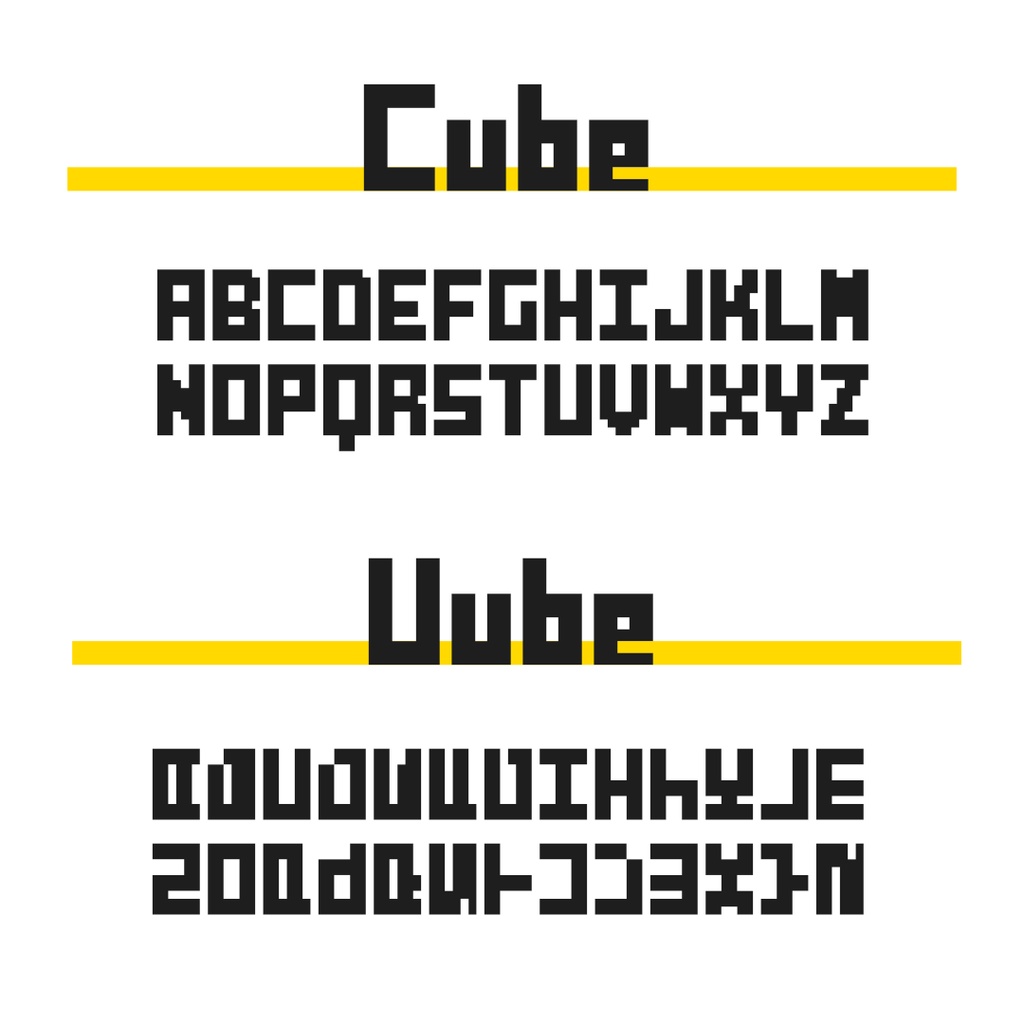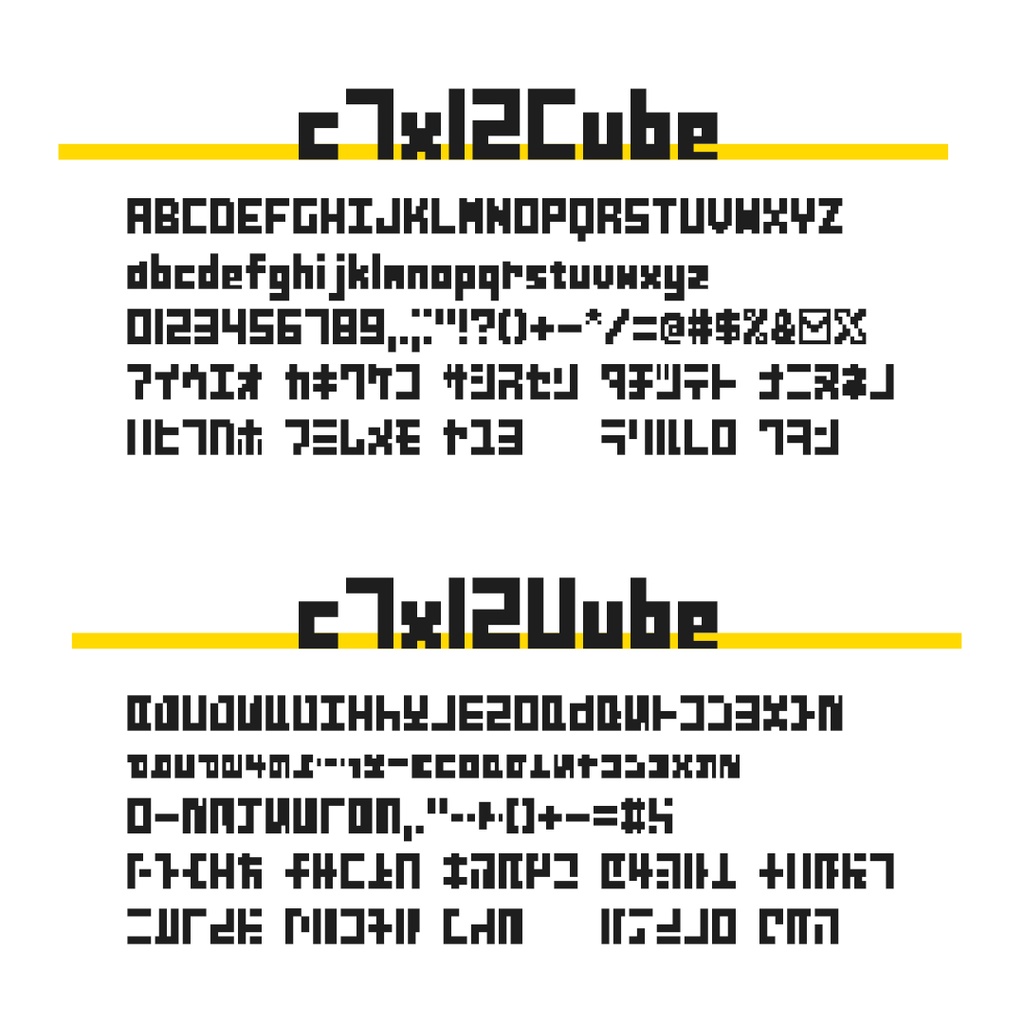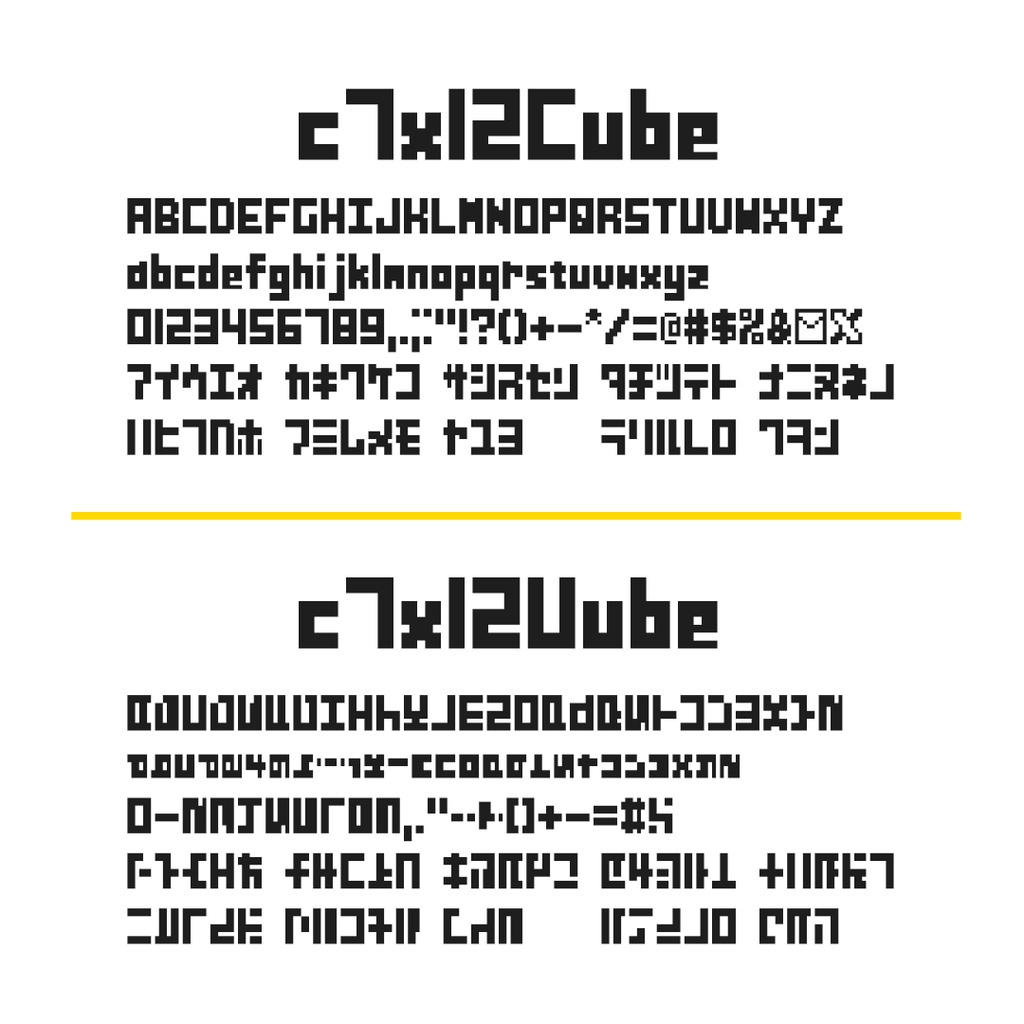
フリーフォント PixelCube
6x9ドットの大文字英数をベースにした、7x12ドットのピクセルフォントシリーズ「PixelCube」です。 英数、カタカナ、一部記号を収録しています。 雰囲気を揃えた2種類のフォントがあるので、用途に合わせてご利用ください。
本シリーズは「c7x12Cube」と「c7x12Uube」の2つのフォントを収録しています。 「c7x12Uube」は、「c7x12Cube」の雰囲気に合わせて文字を左に90度倒したフォントです。